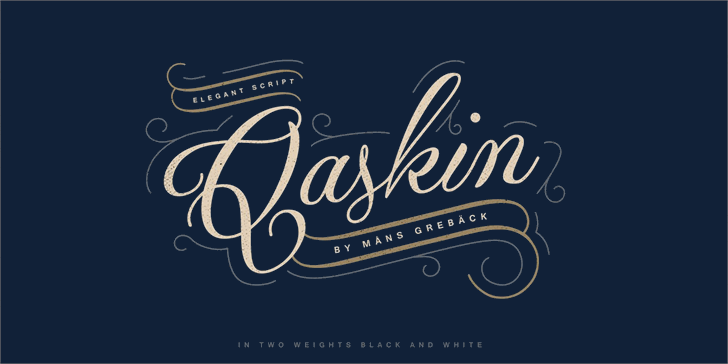
Qaskin Black Font – Download Grátis
A fonte Qaskin Black é uma delicada escolha para qualquer projeto que busque personalidade única e sofisticação. Desenvolvida pelo designer Hamilton, esta fonte script oferece um toque elegante e versátil que torna-a perfeita tanto para uso em sites quanto em materiais impressos. Suas linhas fluidas combinam suavemente com qualquer tipo de design gráfico, seja ele editorial ou comercial. Se procura uma fonte que exalte seu projeto sem comprometer a sua identidade visual, Qaskin Black é um ótimo investimento. Para adquirir uma licença comercial desta maravilhosa fonte, visite o site www.mansgreback.com/qaskin.